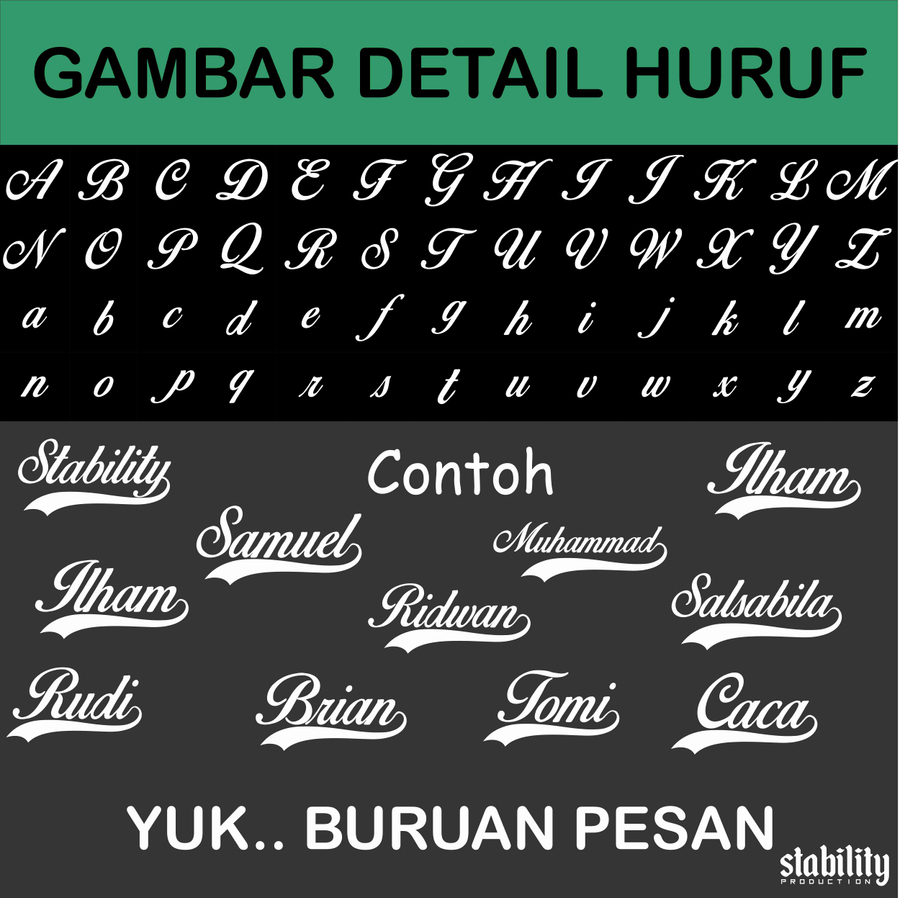
View Font Keren Latin Gif. Di era modern seperti sekarang ini, produk digital menjadi aset penting dalam hidup seseorang. Tipografi yang tepat akan mempercantik desain anda, tetapi jika anda menggunakan sembarang tipografi.
Sebagai seorang designer, tipografi adalah hal yang sangat penting.